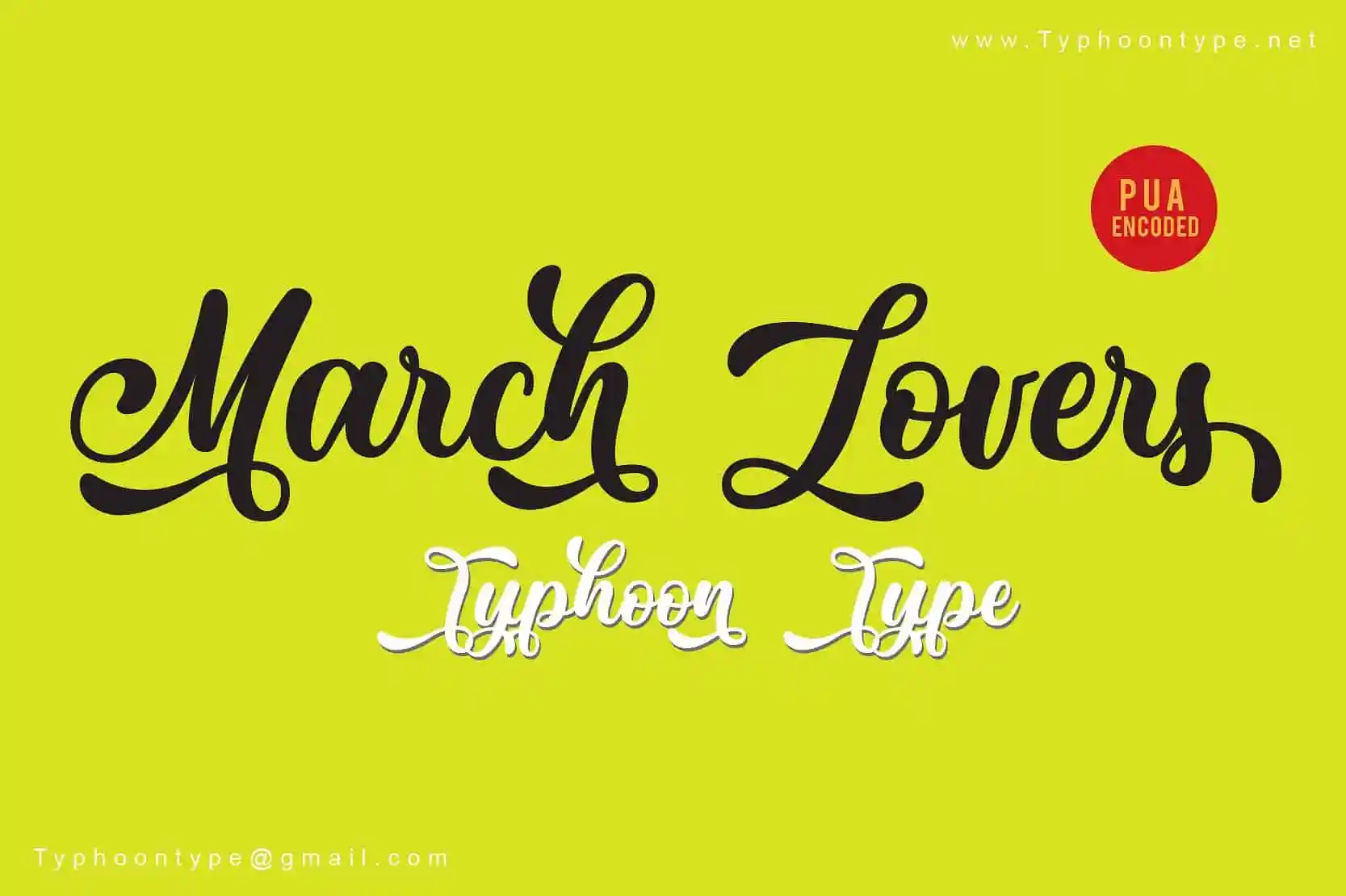
March Lovers Script Font – Download Grátis
Bem-vindo! Introduzimos March Lovers Font! March Lovers é uma elegante fonte script que oferece ascensores e descendentes limpos e formas maiúsculas elegantes. Esta fonte atingirá um padrão de sofisticação, perfeitamente adaptável para diversos usos. Perfeita tanto para gráficos românticos quanto para design editorial, March Lovers se destaca por sua versatilidade e profissionalismo. Não hesite em experimentar essa fonte única, que certamente deixará um impacto no seu projeto.